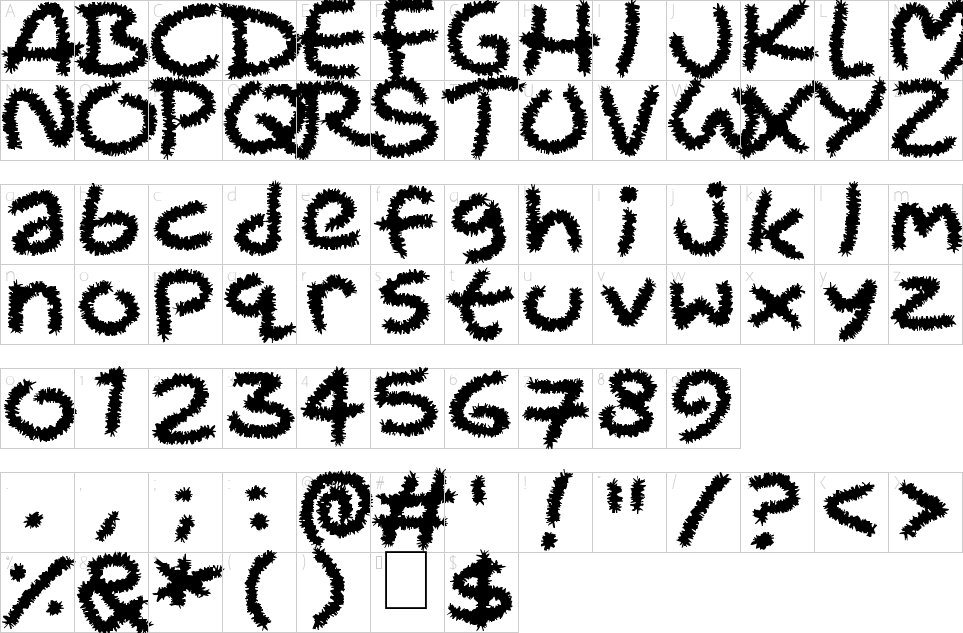
Descubra Pipe Cleaners, uma fonte gráfica que adiciona um toque de criatividade e personalização a seus projetos digitais. Desenvolvida por Darrell Flood, Pipe Cleaners oferece linhas fluidas e versáteis que se adaptam perfeitamente a uma ampla gama de aplicativos, desde layouts de newsletters até criação de materiais educacionais. Com sua simplicidade e modernidade, Pipe Cleaners é uma escolha perfeita para designers e criativos que desejam dar um toque único aos seus projetos. Sua facilidade de uso e alta qualidade de desenho a tornam um recurso valioso na sua biblioteca de fontes. Descubra o poder de Pipe Cleaners hoje e transforme seus projetos de uma maneira única. Com Pipe Cleaners Font | 1001 Free Fonts, você pode experimentar mais sem pagar nada.